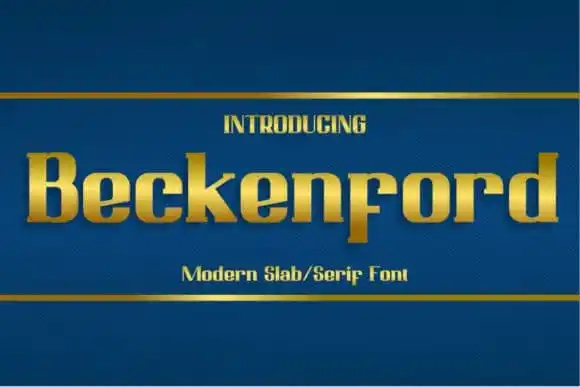
Beckenford Slab Serif Font – Download Grátis
A fonte ‘Beckenford Slab Serif’ é uma combinação única de elegância e vibrante colorido, ideal para qualquer projeto que necessite de elementos brilhantes e chamativos. Essa slab serif typeface é projetada para apresentações, posters ou convites onde você deseja destacar sua proposta com certeza. Com seu design bold e moderno, Beckenford é uma opção perfeita para aqueles que buscam um tipo de texto atraente e distintivo. Além disso, Beckenford pode ser facilmente adaptado a uma ampla gama de projetos, tornando-a uma ótima adição aos seus ideias criativas. Sua simplicidade e brilho garantem que seja fácil destacá-la em qualquer layout ou design. Experimente Beckenford para dar vida à sua próxima criação gráfica!